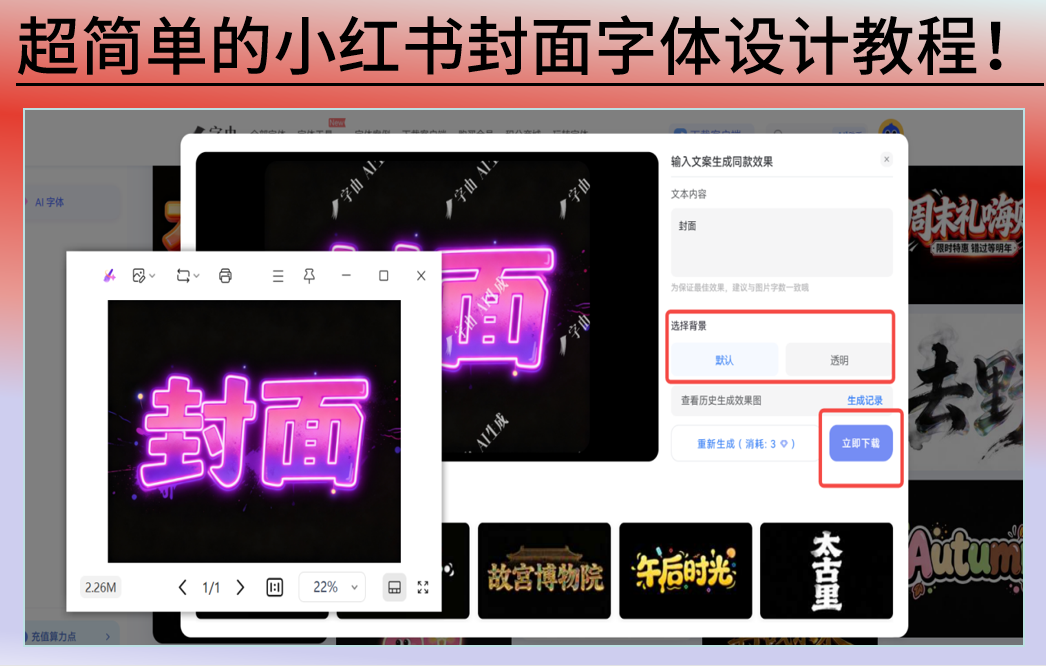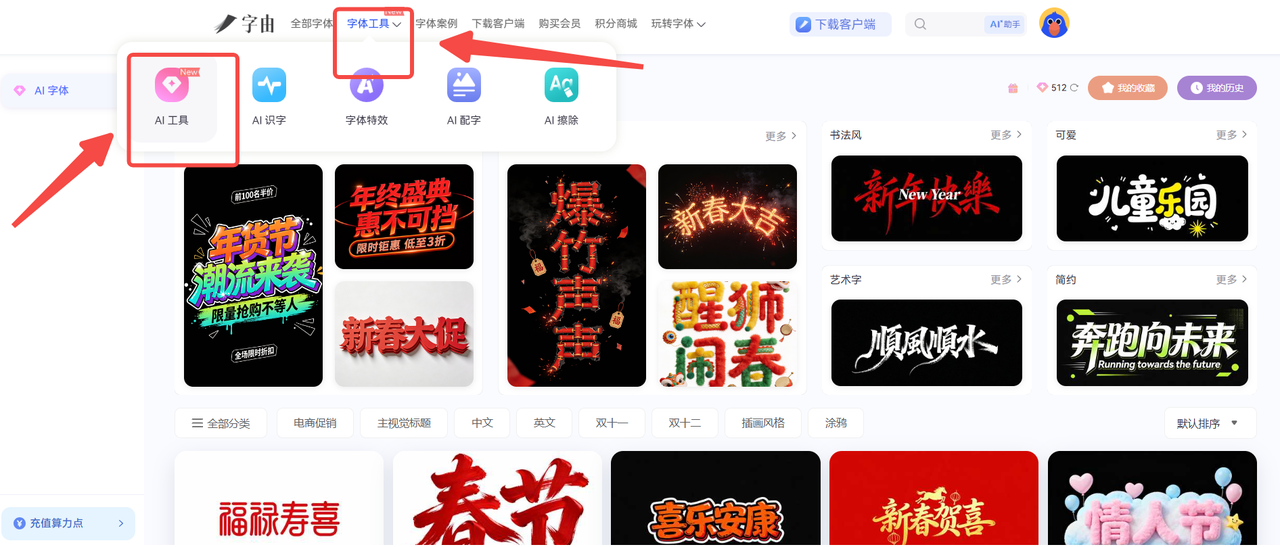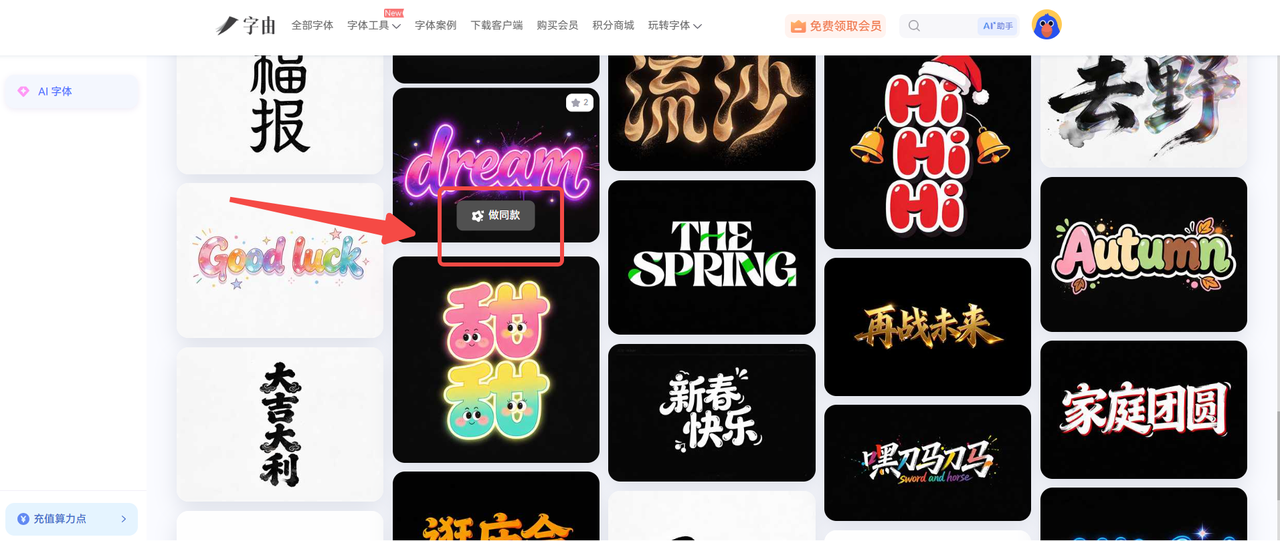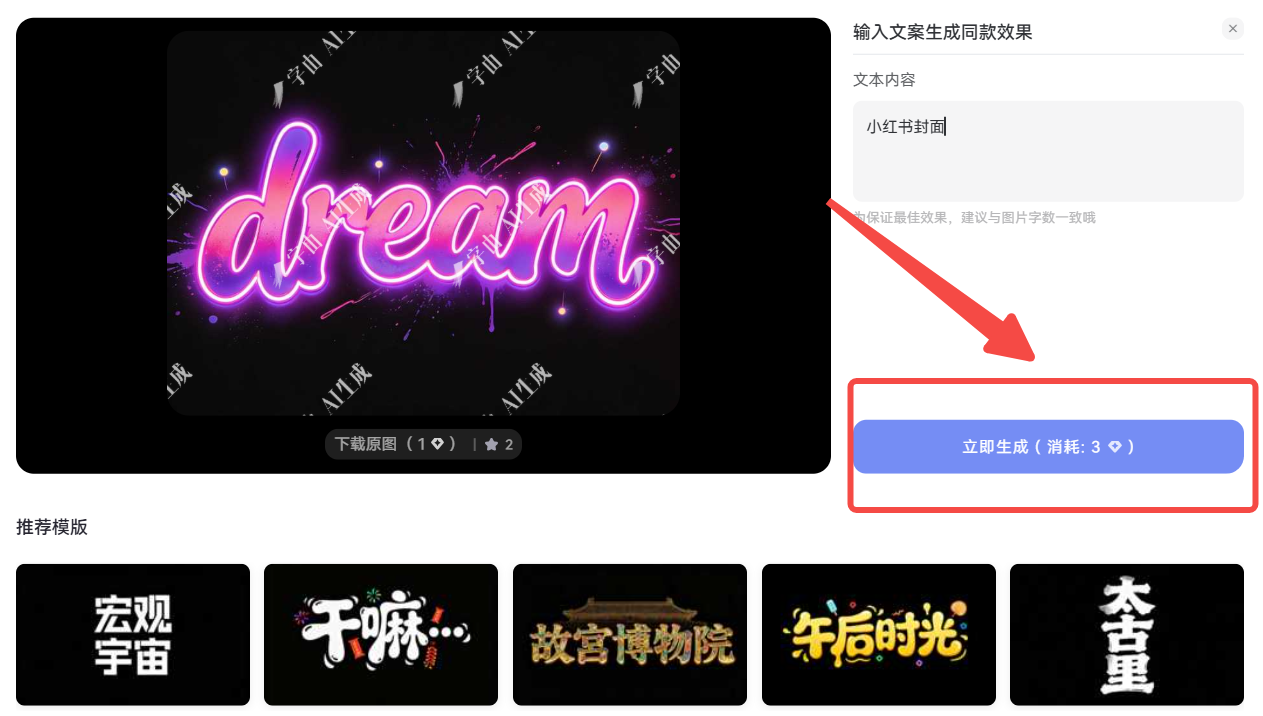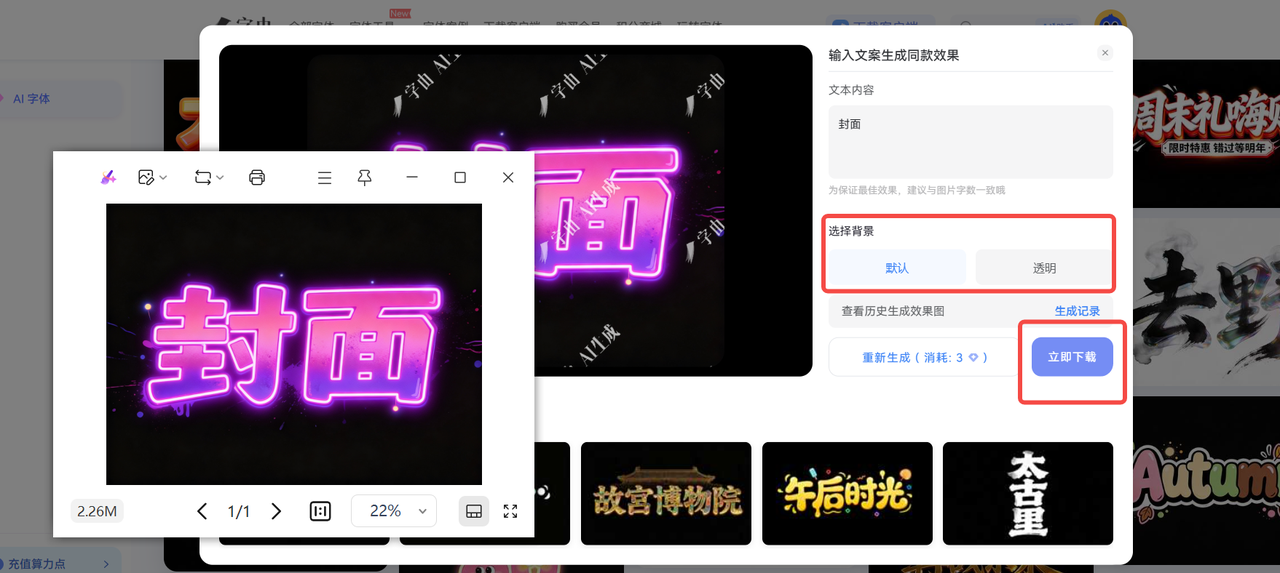
小红书封面字体设计邪修教程,打造独特字体
不了解字体设计专业知识,不会在 Github 中调试小红书封面生成器,该如何做出理想的封面字体设计效果?千万不要错过本文整理的小红书封面字体设计邪修教程!无需手动编辑,只要输入文本内容,等待 25 秒左右就能得到精致的字体设计效果。接下来,本文将为你详细介绍如何借助字由的【AI 字体】功能,一键生成精致的小红书封面字体设计。教程通俗易懂,操作门槛不高,功能也支持免费体验,一起往下看吧!
1、小红书封面独特字体,前往【字由】可一键生成
笔记封面做为给用户呈现的第一道信息,封面设计十分重要,尤其是在小红书这一类比较依靠笔记质量的社媒平台中。而想为封面打造独特的字体设计,抓住用户的注意力,推荐你来尝试一下字由新上线的 “AI 字体” 功能。做为一个有资历,有经验的字体网站,字由除了提供传统的用字方法之外,还上线了 “AI 字体” 功能。不管是社媒字体,还是电商字体,多种字体多种风格,字由均支持一键 Get “同款”。以下是在【字由】中生成独特小红书封面字体的教程,一起往下看吧!
第一步:打开字由官网,访问字由【AI 字体】功能
首先我们要打开字由的官网,在官网导航栏【字体工具】中访问【AI 工具】界面。在此界面,我们就可以使用字由提供的 “AI 字体” 功能了。
界面提供的 AI 字体种类繁多,风格丰富,包含电商用字,社媒字体,书法字,艺术字,简约风和可爱风,为设计小红书封面字体提供了多种选择。
第二步:选中字体,一键 “做同款”
在 “AI 字体”界面,我们可以看到网站采用瀑布流的方式展示了许多精致的字体素材,比如镭射风,彩色字,毛笔字等等。
我们可以在这些字体素材中寻找比较喜欢,或者比较适合做小红书封面的字体素材,之后点击字体卡片上的 “做同款” 按钮。
这里需要注意的是,为了保证生成效果,我们小红书封面文本内容的字数,需要与挑选的字体模板的字数一致,或者小于字体模板的字数。就比如图中挑选的 “dream” 字体模板,它包含 5 个字母,即它允许生成的文本内容字数最大就是 5,输入第 6 个字时会无法输入。所以如果我们小红书封面要承载非常多的文本内容,在生成字体时,可以挑选字数比较多的模板来生成。
第三步:封面字体设计一步到位,支持免费使用
点击 “做同款” 按钮之后,我们就可以打开生成界面。在右上角的文本内容输入框中输入想要生成的文本内容,之后点击 “立即生成” 按钮,等待 25 秒钟左右,字由就会为你生成对应的字体设计了。
第四步:更精致的字体设计效果,可无水印保存到本地
字体生成之后,我们可以按照自己的使用需要来调整
字体效果,比如选择字体的背景。除了字体模板自带的背景设计效果之外,字由还支持生成透明底,只需要在 “选择背景” 那一栏中将背景调整为 “透明” 即可。
调整好字体设计效果,我们就能点击 “立即下载” 按钮,将设计好的字体保存到本地使用了。虽然在字体生成界面会有字由的水印,但下载到本地时是没有添加水印的,后续无需去水印操作。
以上就是本文想提供给大家的小红书封面字体设计的邪修教程了,本文完成封面字体设计主要是借助了字由的【AI 字体】功能。无需掌握专业字体使用操作技能,无需访问 Github 调试代码,在字由【AI 字体】界面中,只需要挑选喜欢的字体设计,然后 “做同款”,25 秒左右就能拥有同样的字体设计效果。不管是有资历的设计师,还是不熟悉字体设计的新手小白,我认为【AI 字体】都可能做为一款提升字体设计效率的工具使用。想拥有精美的字体设计效果,想打造小红书爆款笔记,欢迎前往体验字由【AI 字体】功能。